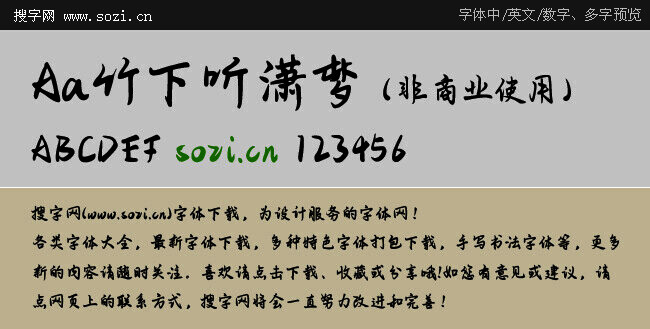
Aa竹下聽瀟夢
搜字網(wǎng)給大家提供一款A(yù)a竹下聽瀟夢(非商業(yè)使用)中文字體下載,該字體是一款中文手寫書法字體,字體書寫自然優(yōu)美,筆畫流暢,結(jié)構(gòu)肆意灑脫,具有很好的視覺感。適合圖書設(shè)計(jì)、包裝設(shè)計(jì)、海報(bào)設(shè)計(jì)等應(yīng)用(此字體為個人非商用版,商用可以聯(lián)系QQ:1006760504)。